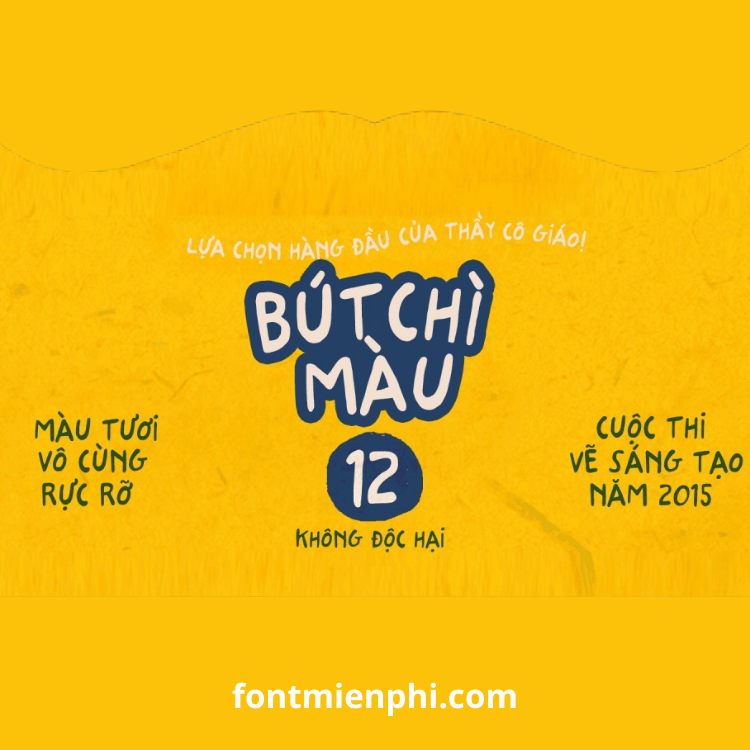
Việt hóa font iCiel Stabile
Việt hóa font iCiel Stabile – Phong Cách Thanh Lịch Cho Thiết Kế Chuyên Nghiệp
Giới Thiệu Font iCiel Stabile Việt Hóa
Font iCiel Stabile là kiểu chữ sans-serif hiện đại với nét chữ cân đối, thanh thoát, mang đến vẻ đẹp tinh tế cho mọi thiết kế. Bản Việt hóa độc quyền tại FontMienPhi.com đã được tối ưu hoá đầy đủ bộ dấu tiếng Việt, giúp bạn tự do sáng tạo mà không lo lỗi font.
Đặc Điểm Nổi Bật
✔ Hỗ trợ tiếng Việt chuẩn Unicode – Đầy đủ dấu, không lỗi font
✔ Phong cách hiện đại, thanh lịch – Hoàn hảo cho branding, tạp chí
✔ Đa dạng kiểu chữ (Regular, Bold, Italic) – Linh hoạt trong thiết kế
Kết Luận